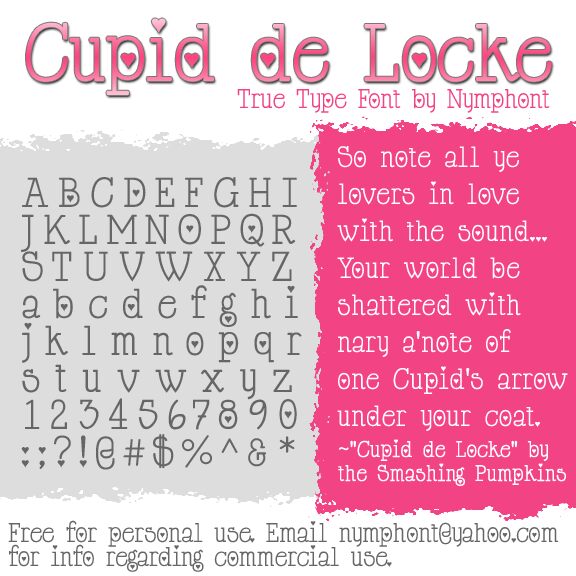
Cupid de Locke autorstwa Lauren Thompson to darmowy krój pisma na Walentynki z lekkim, romantycznym charakterem i klasycznym szeryfowym stylem. Litery są smukłe i pełne wdzięku, a wycięcia w kształcie serc wewnątrz form oraz nad literą „i” dodają całości słodkiego, ręcznie robionego uroku, nie zmieniając jej przy tym w typowy, przesłodzony font.
Świetnie sprawdzi się w papeterii ślubnej, kartkach walentynkowych, metkach prezentowych, opakowaniach butikowych czy nagłówkach kobiecych blogów, gdzie darmowy krój z drobnymi serduszkowymi detalami w prosty sposób podkreśli temat przewodni. Ponieważ ozdoby są wkomponowane w litery, a nie tylko do nich doklejone, font dobrze wygląda też w krótkich nagłówkach, na kartach tytułowych i w monogramach, które potrzebują delikatnego romantycznego akcentu.
Cupid de Locke autorstwa Lauren Thompson to darmowy szeryfowy krój pisma typu display na Walentynki.
Projekt zawiera wycięcia w kształcie serc w zaokrąglonych formach liter oraz kropkę w kształcie serca nad „i”.
Casual & informal slab serif with "Heart" accents designed & made into font form by by Lauren Thompson, "Nymphont" July 8, 2009. Inspired to create this typeface after creating a decorative hand-drawn slab serif font, "LT Chickenhawk." The traditional version (ie sans "hearts") is called HappyPhantom